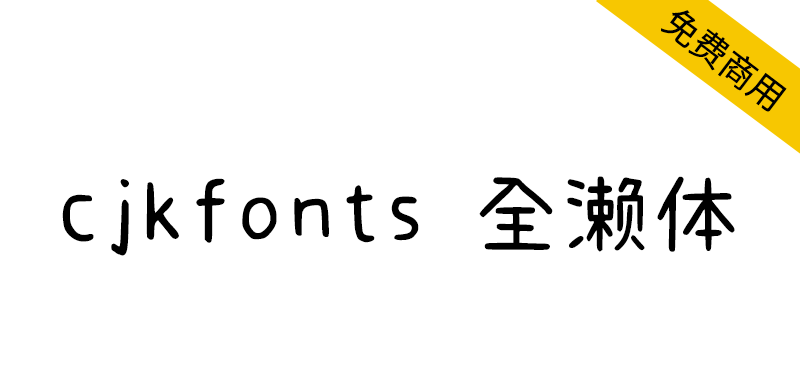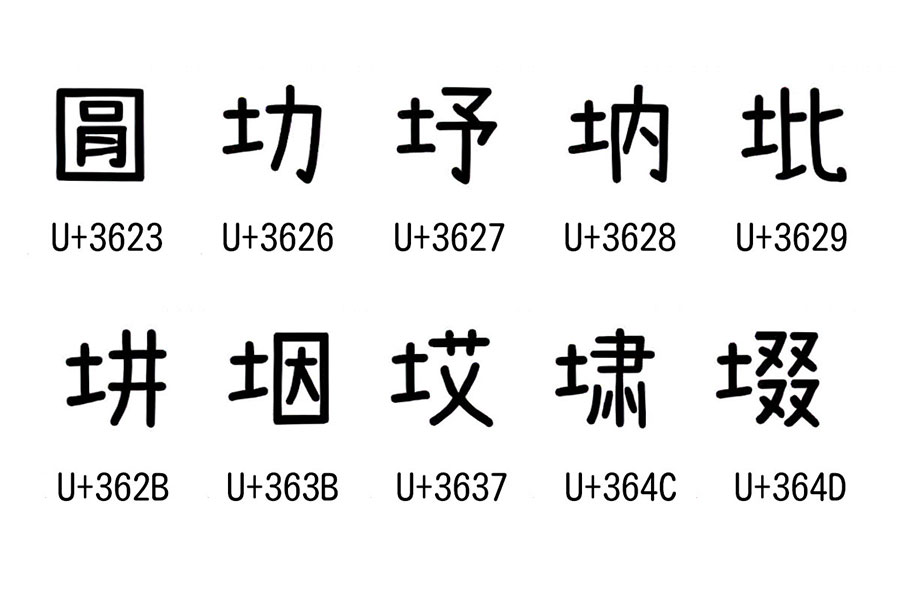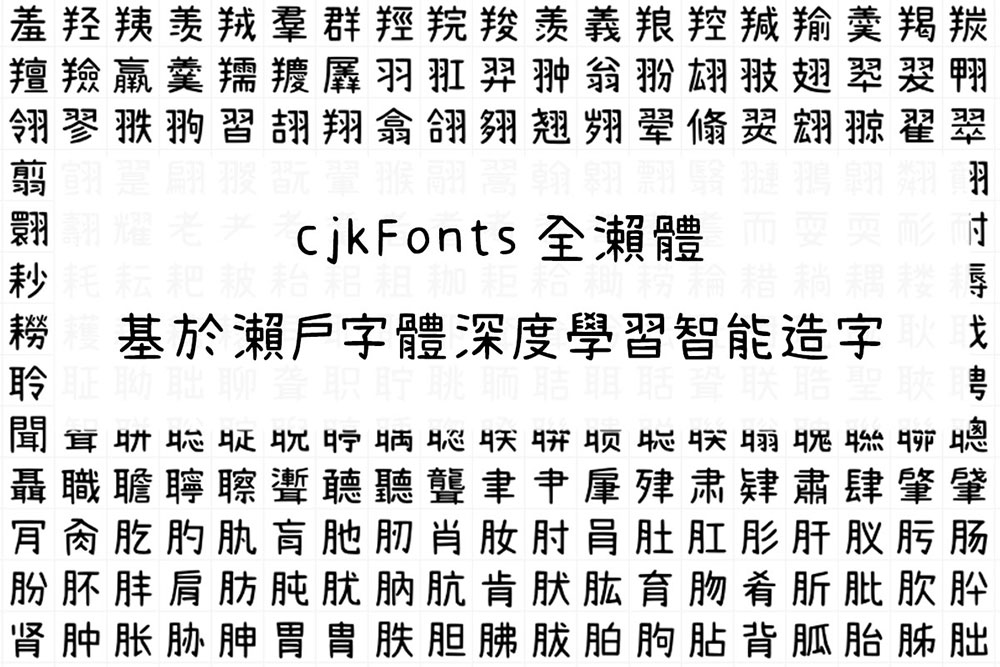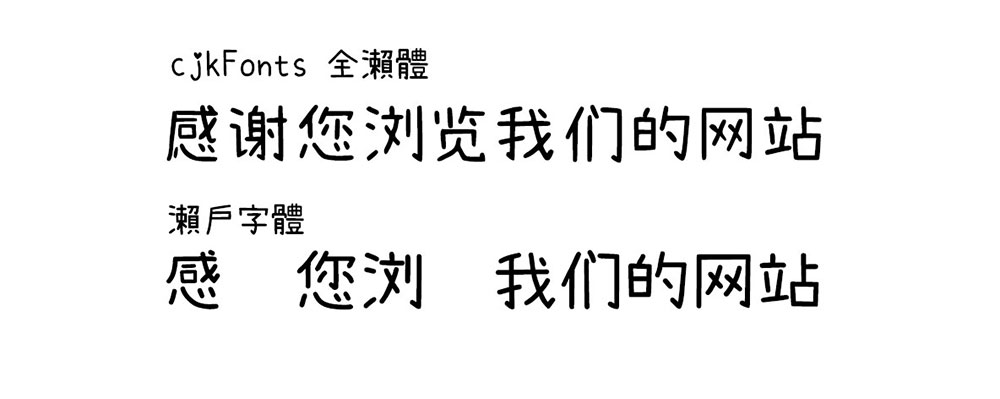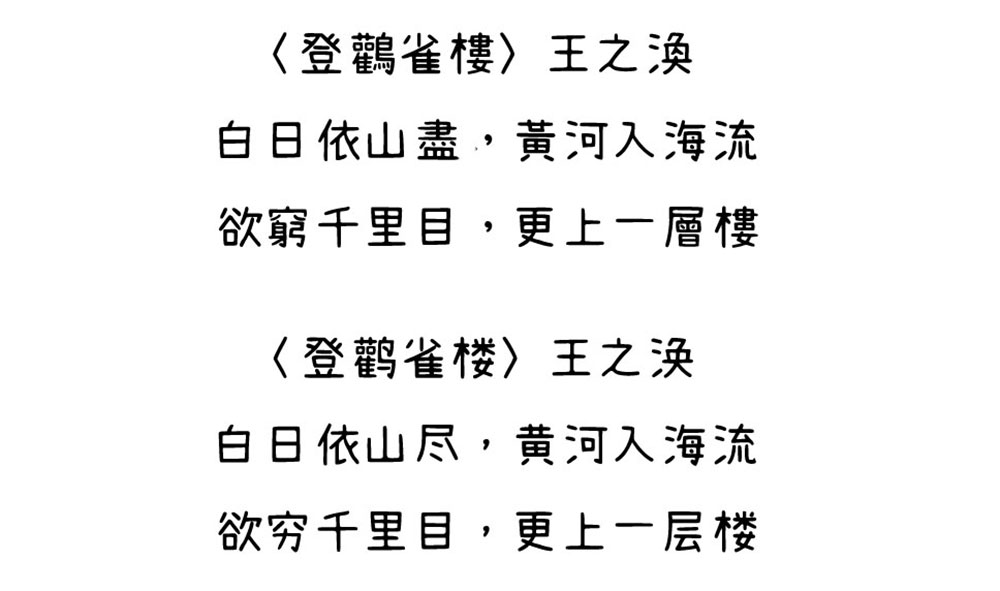
cjkFonts全濑体是基于濑户字体透过深度学习智能造字,产生的字体数量是跟思源黑体相同,所以是全面支持繁简日韩字体,弥补了濑户字体没有的繁体及简体字,可以安心使用,不会遇上缺字的情况。
由于是电脑学习了字体的特点及风格后,每个字根据学习后的数据造字,所以字体的风格会跟濑户字体有轻微的分别。以下是造字的过程:
1、深度学习训练:这过程是教电脑学习字体的特点及风格,就像教小明友学写字一样。电脑要24小时不停训练,一般训练3至4天,初步字体成形。
2、调整字体:训练完成后,检视产生的字体,如果有变形的情况,就人手修正。
3、再训练:修正后的新字体,再加入训练,重复步骤一,让机器学习新的字体特点。
4、再训练:反复一至三的步骤,当产生的字体达到满意效果,然后就可以产生全部字体。
5、筛选及调整:产生的字体数量大约4万2千个字左右,当中会有一些字是变形的,要筛选出来再人工调整,这个步骤工作量是非常大及花费大量时间的。
6、输出字体档案:使用软件组合字体,然后输出字体档案(ttf)。
这些全部都是新字体,濑户字体没有这些字的,这些字体是没有作出任何修正,都是直接电脑造出来,效果都很好。
造出一款字大约要用3至4个月时间,如果人手充足的话,可以缩短至2个月。濑户字体的数量已足够应付一般情况,为何要基于它再造字?
濑户字体是一款很可爱的手写字,在繁体支持上是很足够的,但是在简体字上,缺字情况严重,很多日常会使用到的字也缺少,我们希望可以补回缺少的简体字,使繁体及简体的应用上也可以使用此字体。